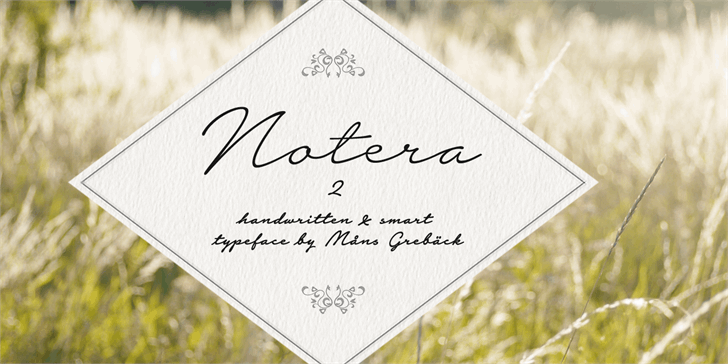
Na categoria de fonts script, apresentamos a Notara 2, uma criação cuidadosamente feita por Måns Grebäck em 2018 para ser uma versão recriada do popular Notara. Com seu estilo retrabalhado e extenso conjunto de símbolos, Notara 2 se torna um tipo de escrita autêntica, ideal para uso em diversos idiomas. Seu extenso arsenal inclui recursos de tipos aberto que permitem uma variedade impressionante de alternativas para letras contextualizadas e estilísticas, criando um estilo verdadeiramente manuscrito. Junto com a fonte regular, Notara 2 Underline é outra opção inclusa. Esta fonte serve como um excelente recurso para sobrecaracteres e enfatiza visualmente o texto. Notara 2 oferece cinco pesos (Espesso, Bold, Medium, Light e Espeso), cada um proporcionando uma nova experiência de design gráfico. Agora é sua vez de explorar a versão personalizada e versátil da Notara – notara 2 Script Font. Com suas ferramentas de estilo aberto e alternativas contextualizadas, você poderá aplicar este tipo de escrita ao seu projeto, dando-lhe um toque único e autêntico.